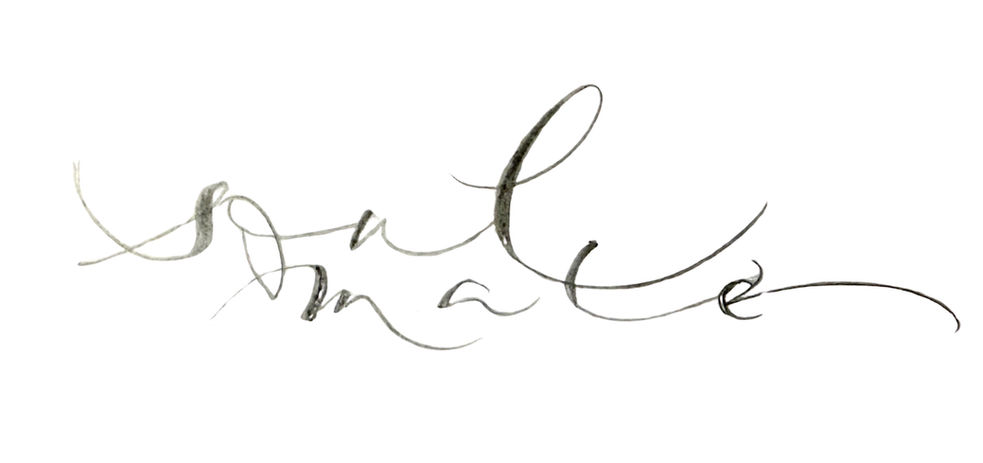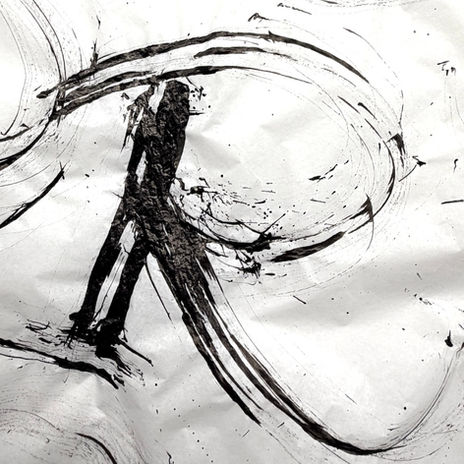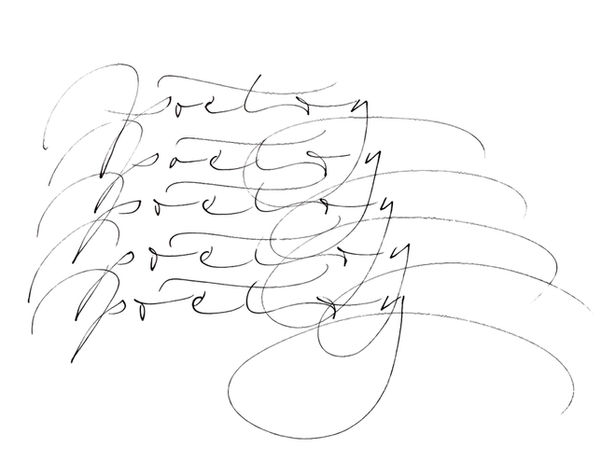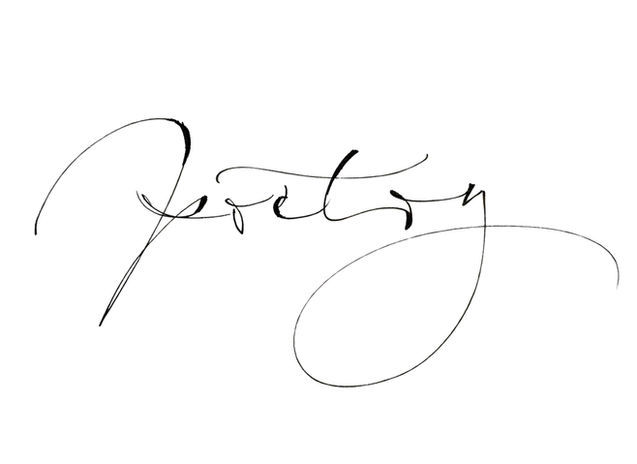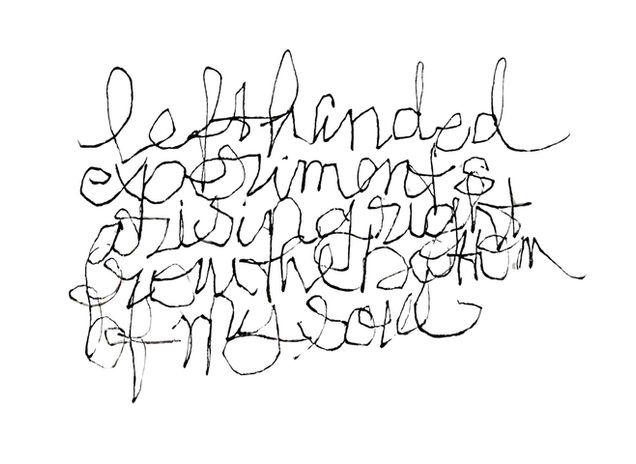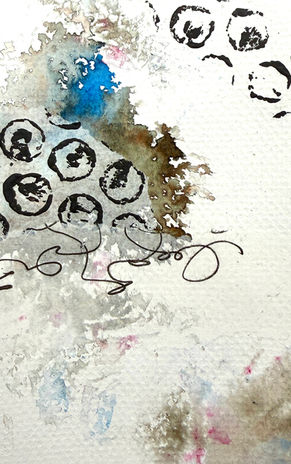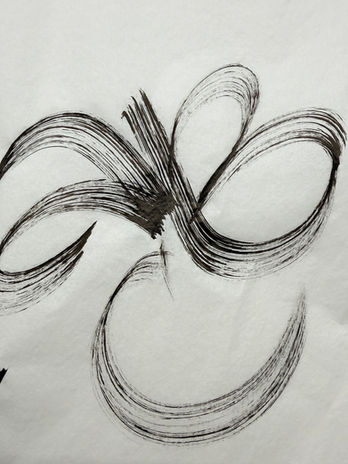
Kalligrafische Gestaltung im Miniformat (kreative Schreibwerkzeuge)
Gertrud Schetelig
Kalligrafische Gestaltung im Miniformat
Kreative „Schreibwerkzeuge“ wie Strohhalme, Balsaholz und kleine Ästchen kommen zusammen mit ungewöhnlichen Stempelmaterialien zum Einsatz, wenn wir die drei Elemente erkunden, die Wassily Kandinsky seiner Gestaltungstheorie zugrunde legte: Punkt, Linie und Fläche.
Zusammen mit skripturalen Schriftelementen & rhythmisch geschriebenen Worten entstehen kleine Serien, die alle das Thema „Hand-Schrift“ in den Fokus stellen.
Techniken:
Collage, Stempeldruck, Schreiben etc.